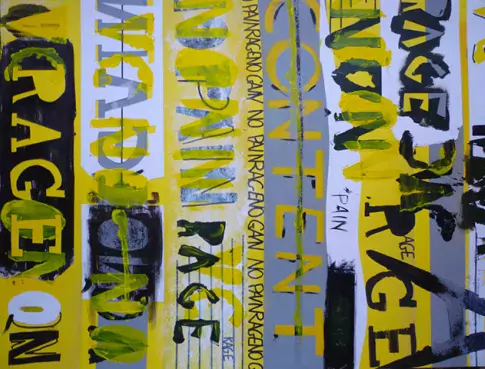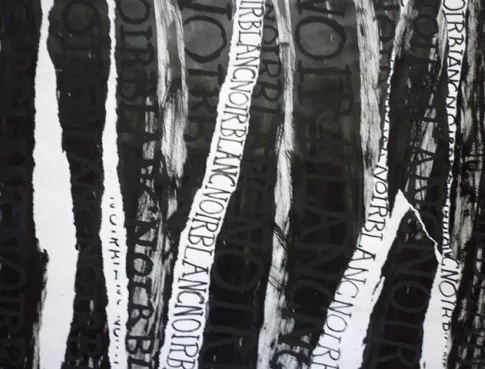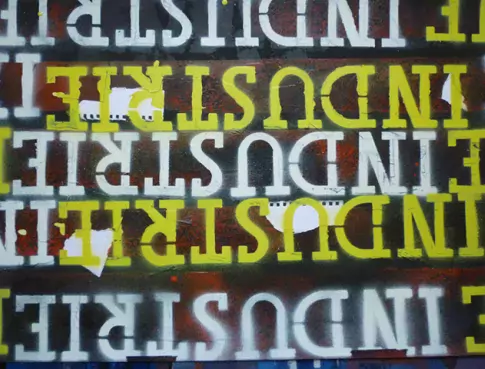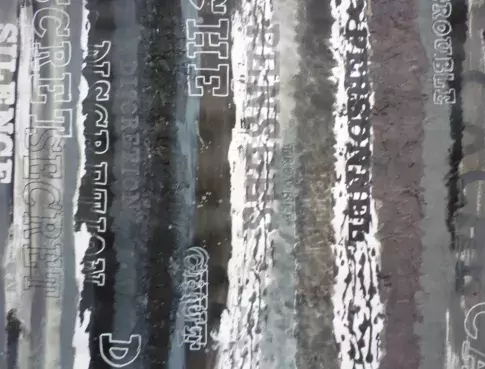
Par l'accumulation, la superposition et la juste lisibilité typographique, les étudiants de MANAA de l’ école d’art de Toulouse ont réalisé un travail d'expression plastique (convocation d'opérations plastiques diverses).
Inspirées par les oeuvres de Neville Brody, leurs réalisations se situent d'une part dans une démarche de peintre lettriste futuriste tel que Marinetti, mais également dans un graphisme post-moderne et contemporain.